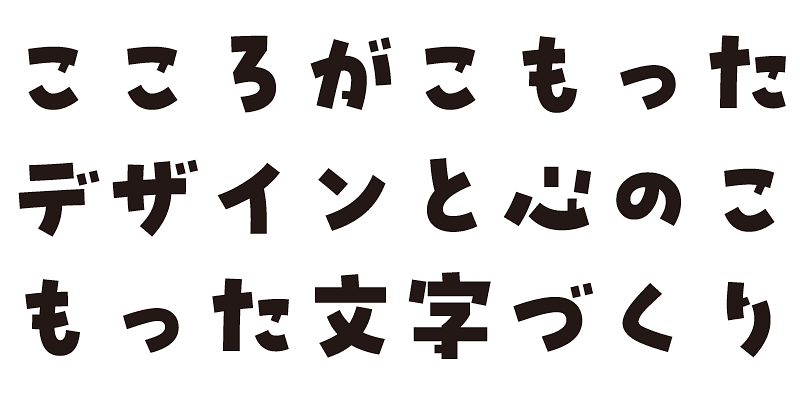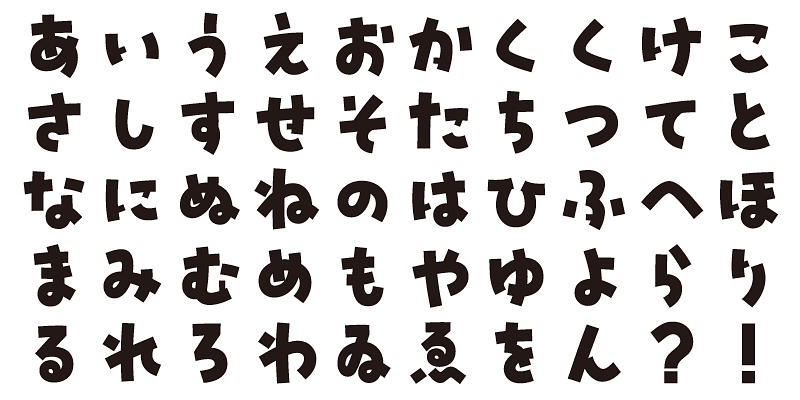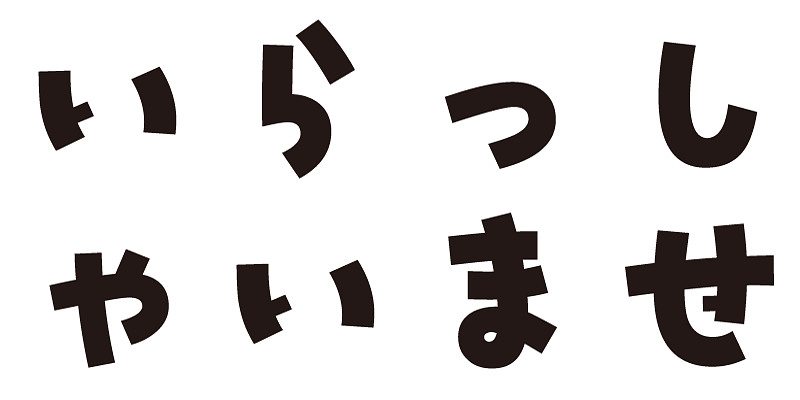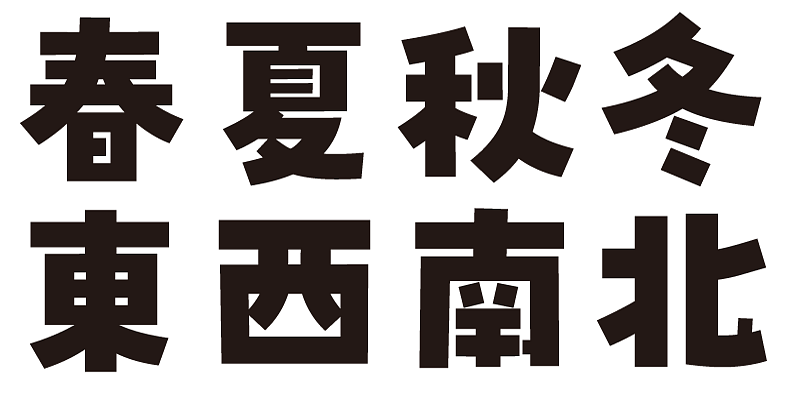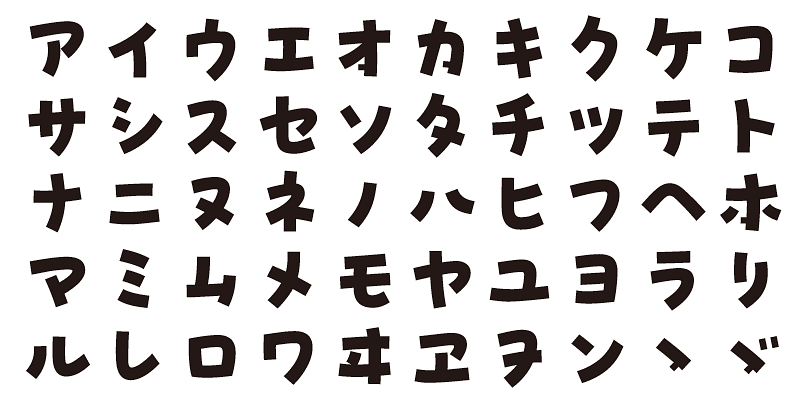
優しくもダイナミックなゴシック (sans-serif) スタイルの書体です。
この書体ファミリーの各フォントには、1,000 個の漢字のほか、ひらがな、カタカナ、英数字、句読点が含まれています。
言葉を文字で伝えるとき,その言葉の背景も一緒に伝える事ができれば、と思い制作しています。ここちよさ,楽しさ、気持ちよさを感じてもらえればと思っています。